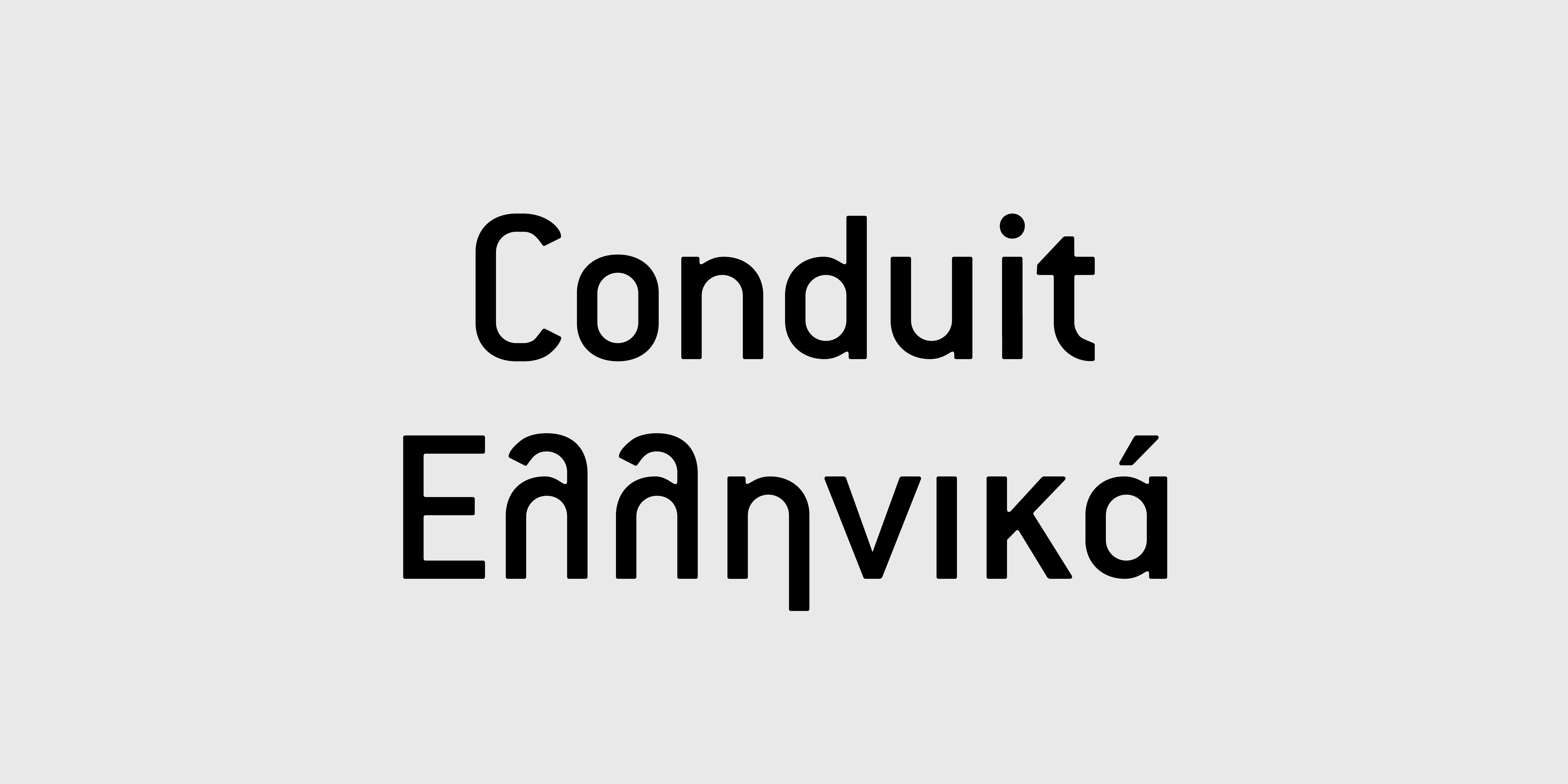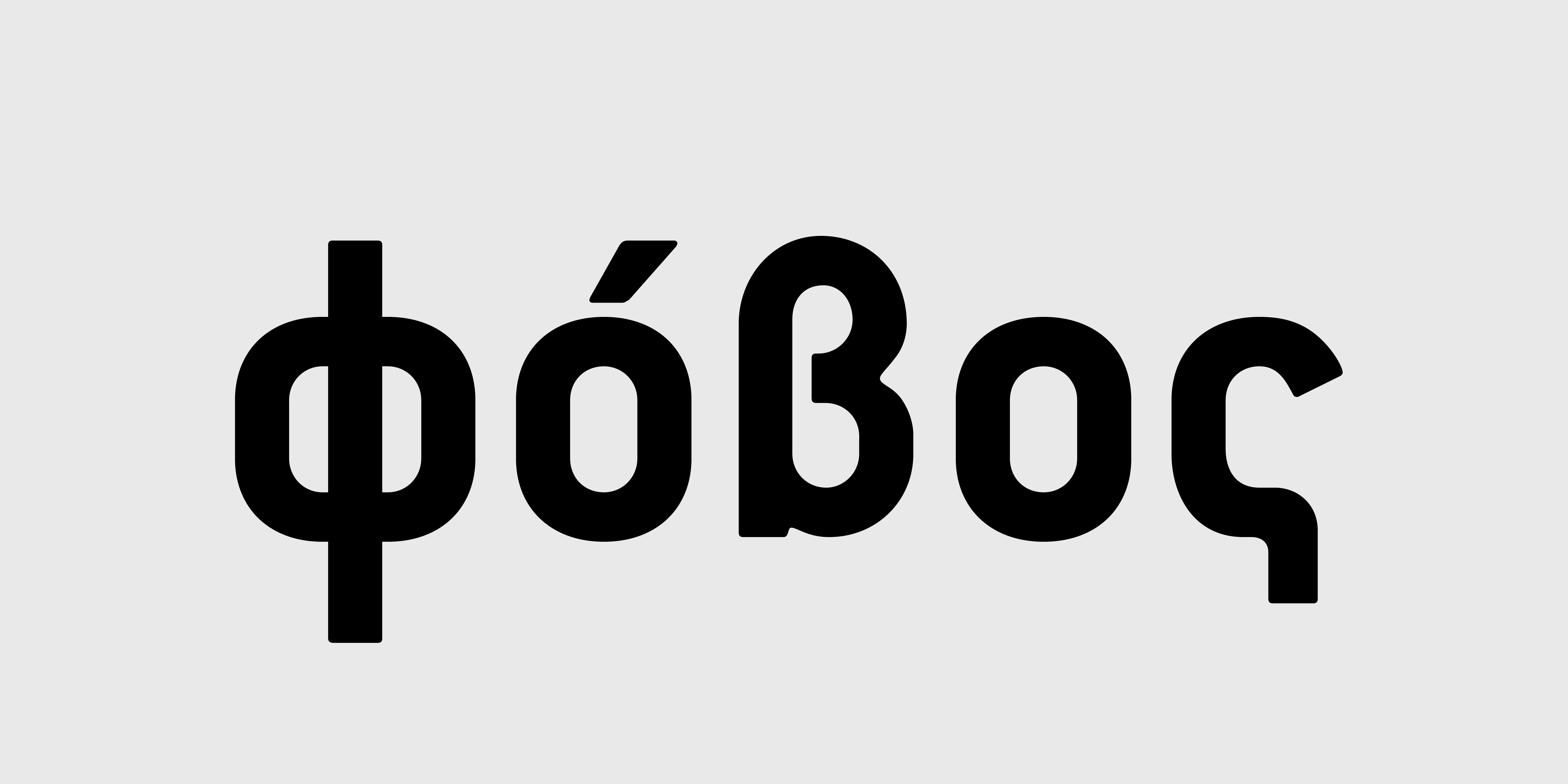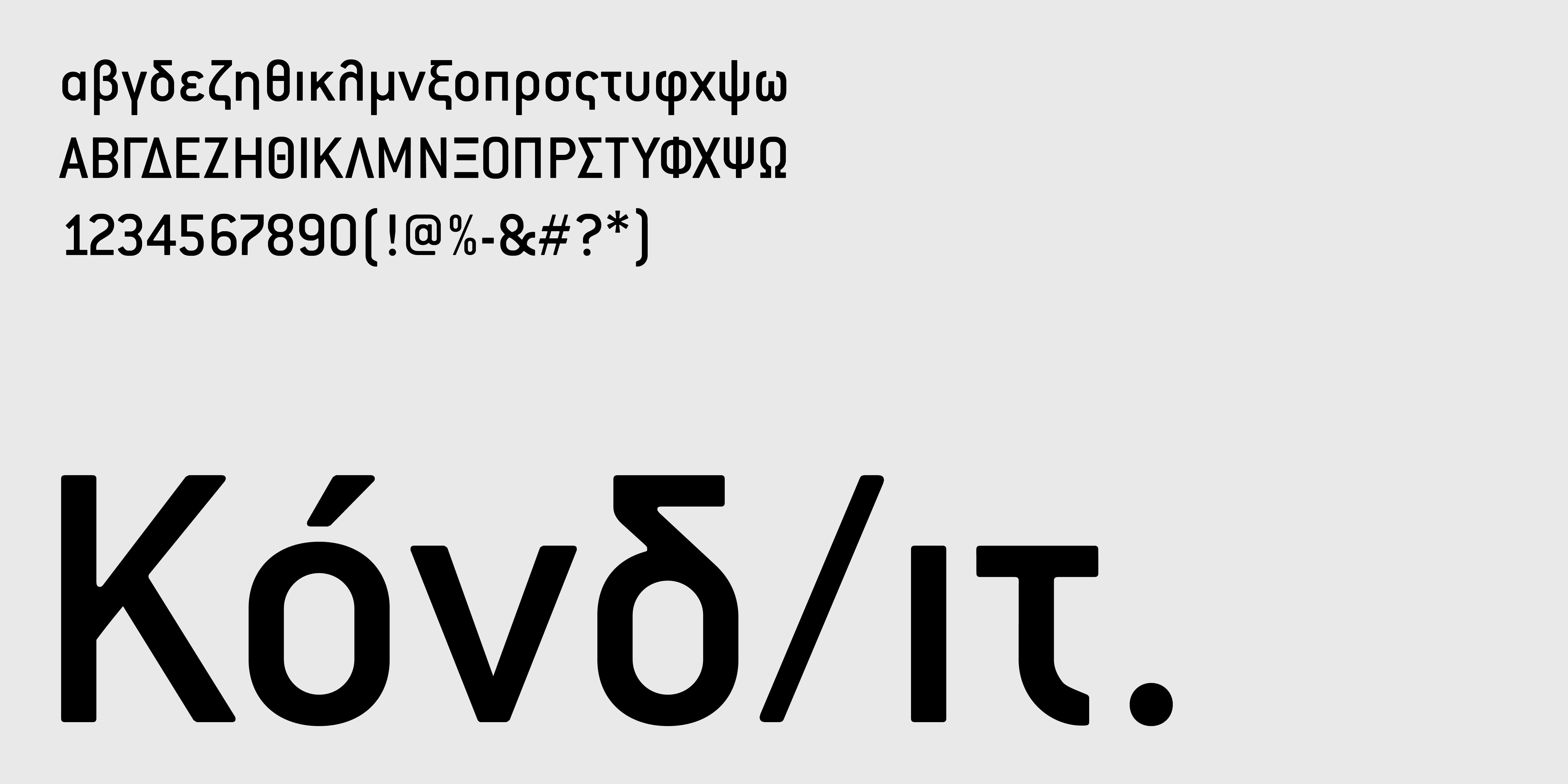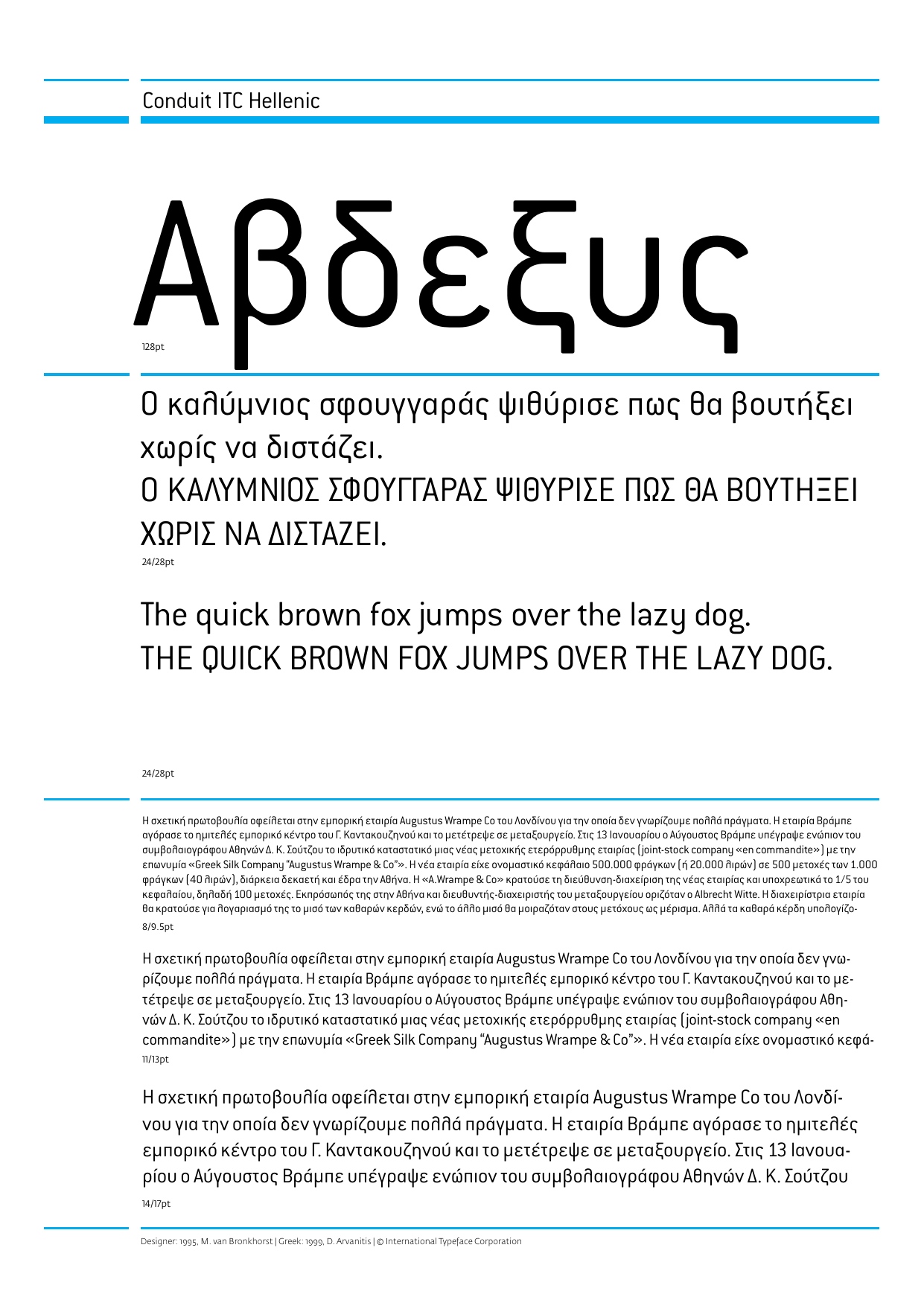
Conduit ITC Ελληνικά
Βασισμένη σε γράμματα επιγραφών φτιαγμένων από ερασιτέχνες. Ο σχεδιαστής πήρε τις απλές αλλά παράξενες φόρμες γραμμάτων και προσέθεσε την εμπειρία του πάνω στο σχέδιο και τις αναλογίες παραβιάζοντας στην πορεία σχεδόν όλους τους κανόνες. Οι φόρμες των γραμμάτων σχεδιάστηκαν με βάση έναν κάνναβο με όλες τις άκρες και τις γωνίες στρογγυλεμένες. Μετά από λίγες οπτικές διορθώσεις δημιουργήθηκε η ITC Conduit, μια σχετικά στενή, τετράγωνη και σαφώς αναγνώσιμη ισόπαχη γραμματοσειρά. Σχεδιαστής Mark Van Bronkhorst, Ελληνική έκδοση Δημήτρης Αρβανίτης